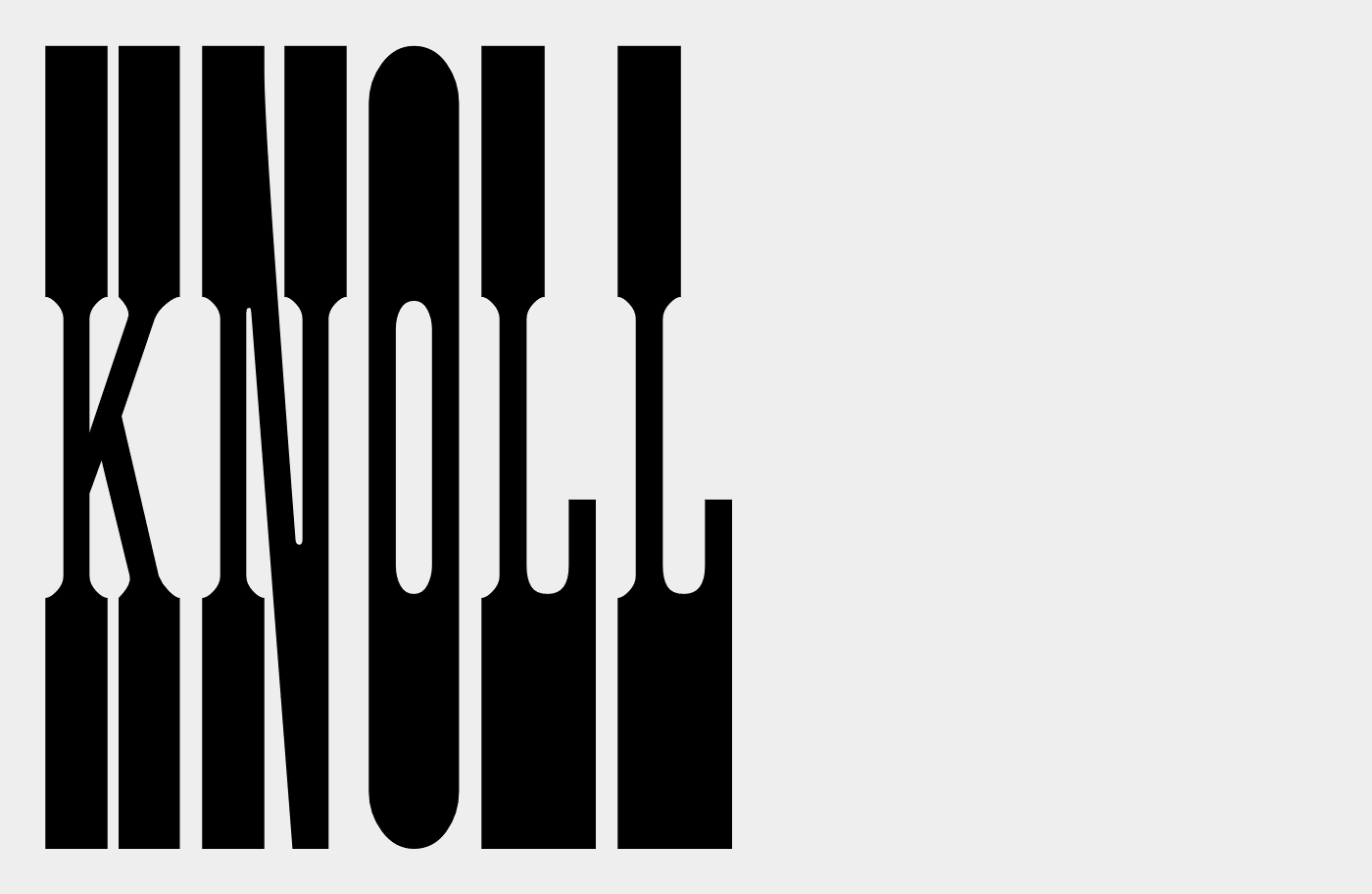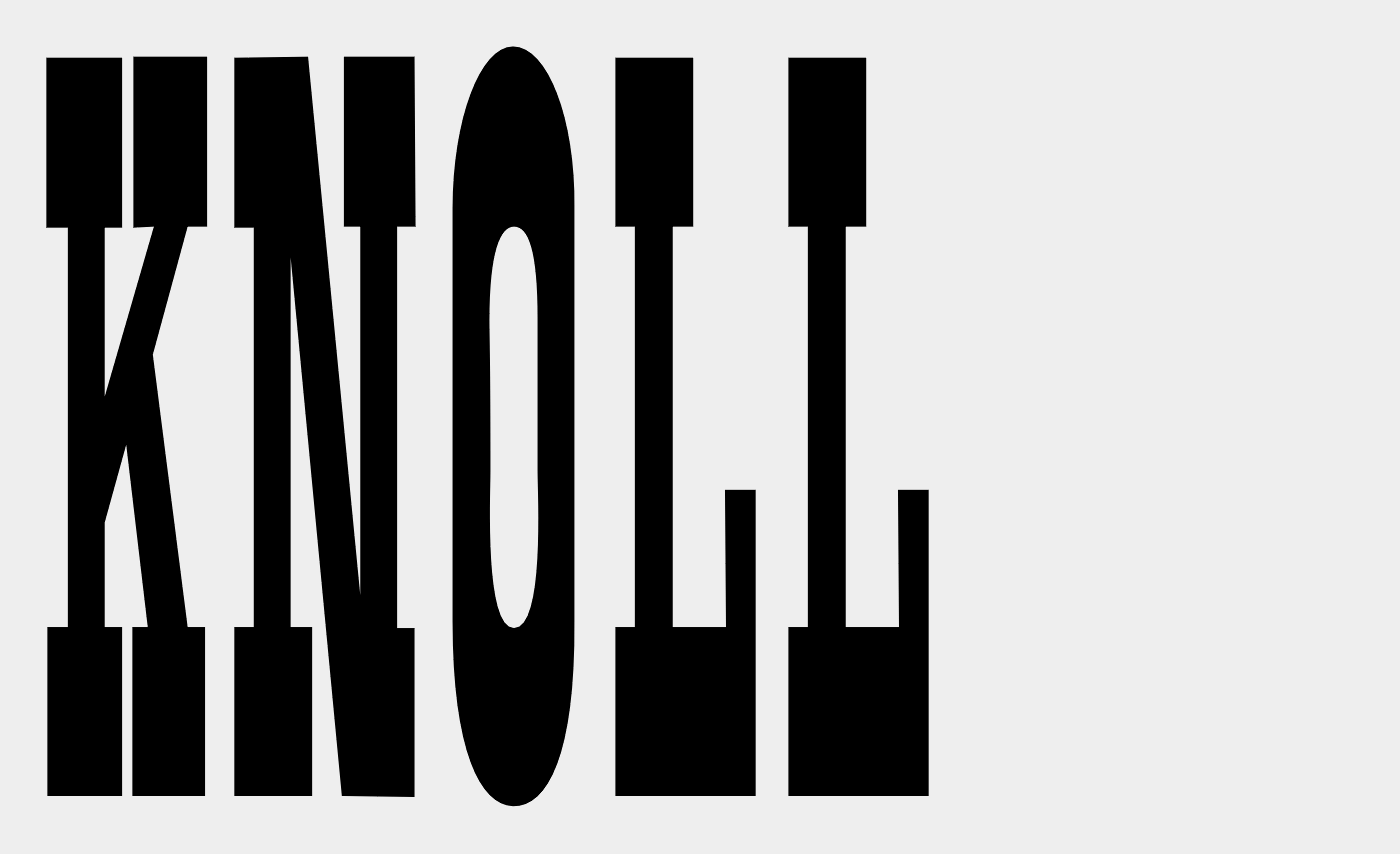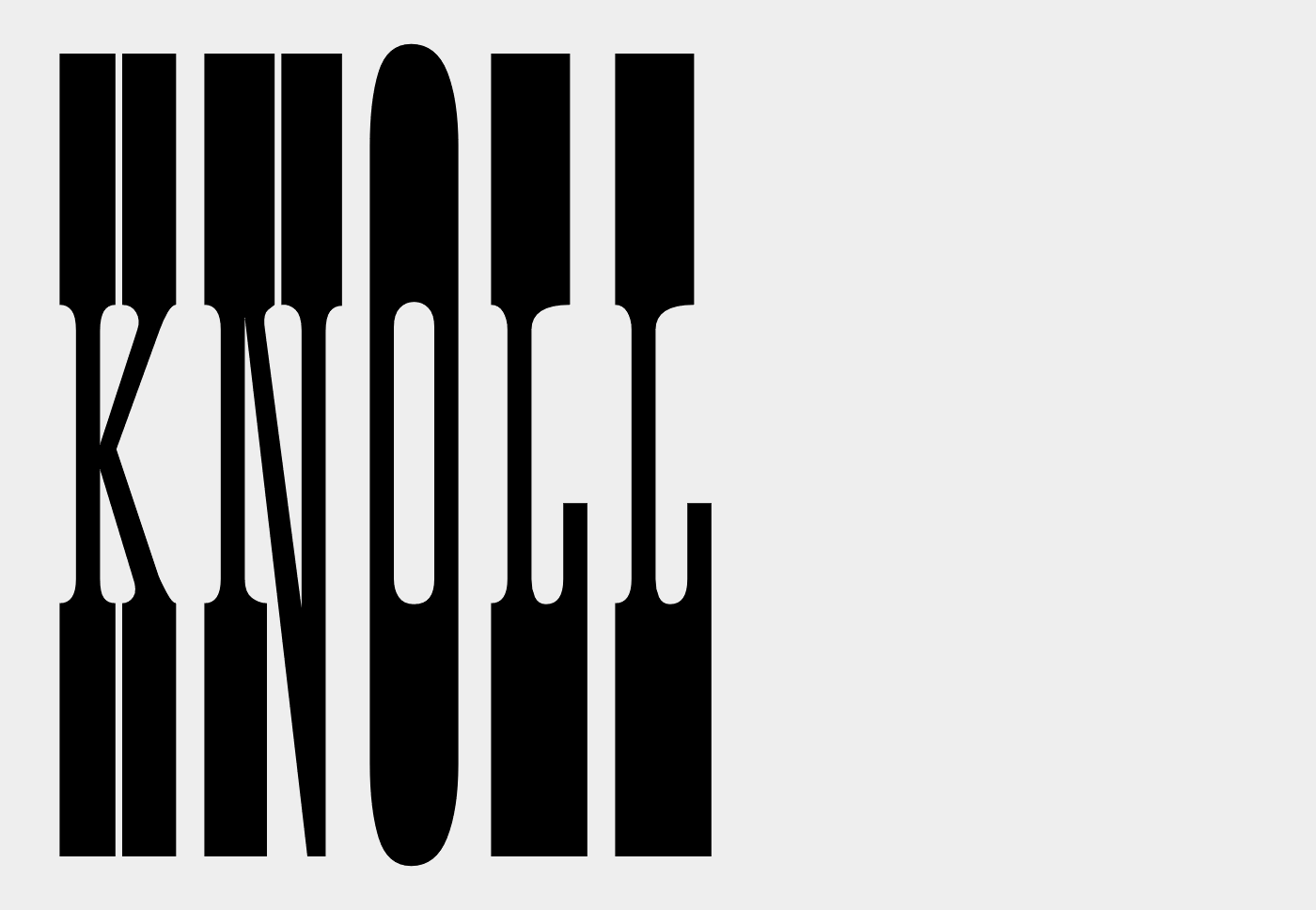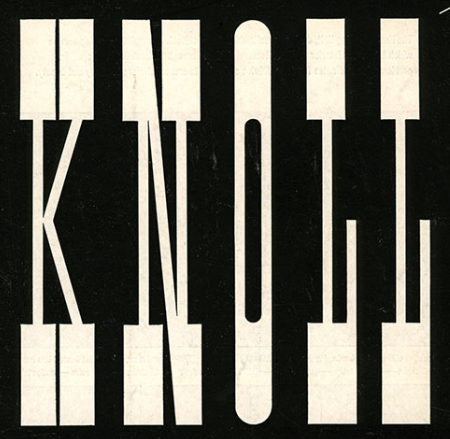
Schriftart von altem KNOLL-Logo
ich bin vor einigen Tagen auf das alte Logo der Firma KNOLL gestoßen. Mir kam es sofort bekannt vor und ich war mich sicher, ich hätte so eine Schrift schon einmal gesehen. Nun habe ich meine komplette Schriftbibliothek durchforstet und es war nichts dabei, was annähernd so prägnante Serifen hat und gleichzeitig so gedrungen ist. Auch online war nichts zu finden.
Hat jemand vielleicht eine Idee, um was für eine Schrift es sich hier handeln könnte?
Noch eine kleine Info am Rande. Das Logo wurde 1947 von Herbert Matter gestaltet.
Das sind sogenannte Old Western Style Fonts.
Ich vermute, dass das eine bearbeitete Ponderosa ist:
Ansonsten vielleicht eine gestauchte und bearbeitete Old Towne?
Edit 1: Es könnte aber auch sein, dass das Logo nicht auf einer Satzschriftart basiert (was ich auch am meisten vermute), da man früher entweder von Hand gezeichnet hat oder Buchstaben-Schablonen verwendet hat.
Das ist doch schon die Antwort. Es wurde »gestaltet«, nicht »aus einer Schrift gesetzt«.
Das hatte ich doch glatt übersehen... :-). Naja, in Edit 1 habe ich ja auch schon vermutet, dass das Logo nicht auf einer Satzschriftart basiert.
Umgekehrt ist es durchaus möglich, das die recht ähnlichen existierenden Schriftarten von solchen handgezeichneten Logos aud der Vor-Digitalfont-Zeit inspiriert wurden.
Ich habe ja auch schon aus einen einst speziell für ein Logo gezeichneten Buchstaben, so Hardman, Incopins Clusters, Kaufhalle, Maass Slicer und Spartakus, weitere könnten da durchaus folgen.
Die Buchstaben wurden bestimmt von Herbert Matter, wie hier schon vermutet wurde, speziell für das Logo gestaltet.